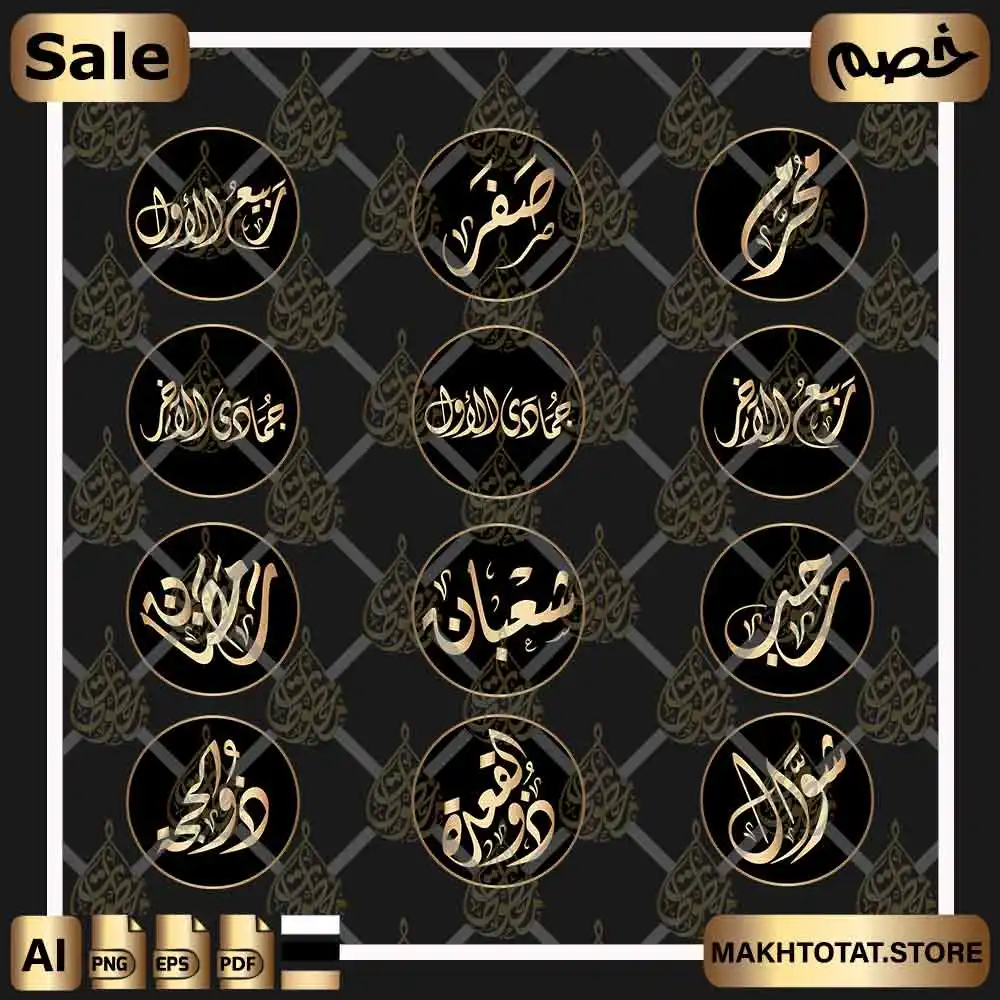
استفد من مخطوطة شهر شعبان
شهر شعبان مخطوطة مزخرفة متوفرة الآن، تستطيع استخدمها في تصميمك، أو لعمل مونتاج إذا كان عملك يخص شهر شعبان، فهو من الشهور المباركة التى يُستحب فيه إكثار الصيام، فعن عائشة رضي الله عنها، قالت: كان رسول الله صلى الله عليه وسلم ” يصوم حتى نقول: لا يفطر، ويفطر حتى نقول: لا يصوم، فما رأيت رسول الله صلى الله عليه وسلم استكمل صيام شهر إلا رمضان، وما رأيته أكثر صياماً منه في شعبان ” رواه البخاري ومسلم.
نُبذة بسيطة عن مخطوطة شهر شعبان
مخطوطة شهر شعبان مزخرفة بخط الثلث ذات ألوان حية ومختلفة، لذلك يمكن التصفح هنا عبر متجرنا ،واختر ما تريد من نموذجين من مخطوطات شعبان، أو الأشهر الحرم، أو مخطوطات ذات عبارات إسلامية أخرى، وحتى تضمن جودة التصميم فى ڜهر شعبان، الحروف ترسم و تزخرف بأشكال هندسية ، ذات ألوان مختلفة ومتناسقة، مثل الأسود، والذهبي المدرج ،وغيرها من الألوان التى تُرح العين، حتى تحصل على تصميم شهر مخطوطة شعبان بشكل متكامل.
هل المخطوطة متوفره بشكل أخر؟
هل بقية أسماء الشهور العربية متوفرة؟